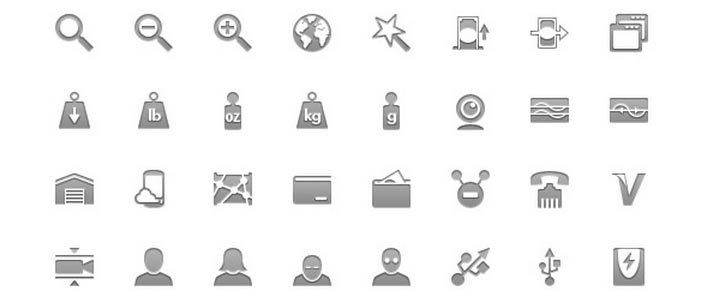
Font Free per Web Designer: Adec
Continuiamo la nostra raccolta di font  per web designer con Adec, un font davvero “strano” ma allo stesso tempo innovativo e gratuito.
Il font Adec è davvero particolare, può essere odiato o amato ma sicuramente vi farà “emergere” dalla solita routine.
Come sempre ecco una breve anteprima del font: